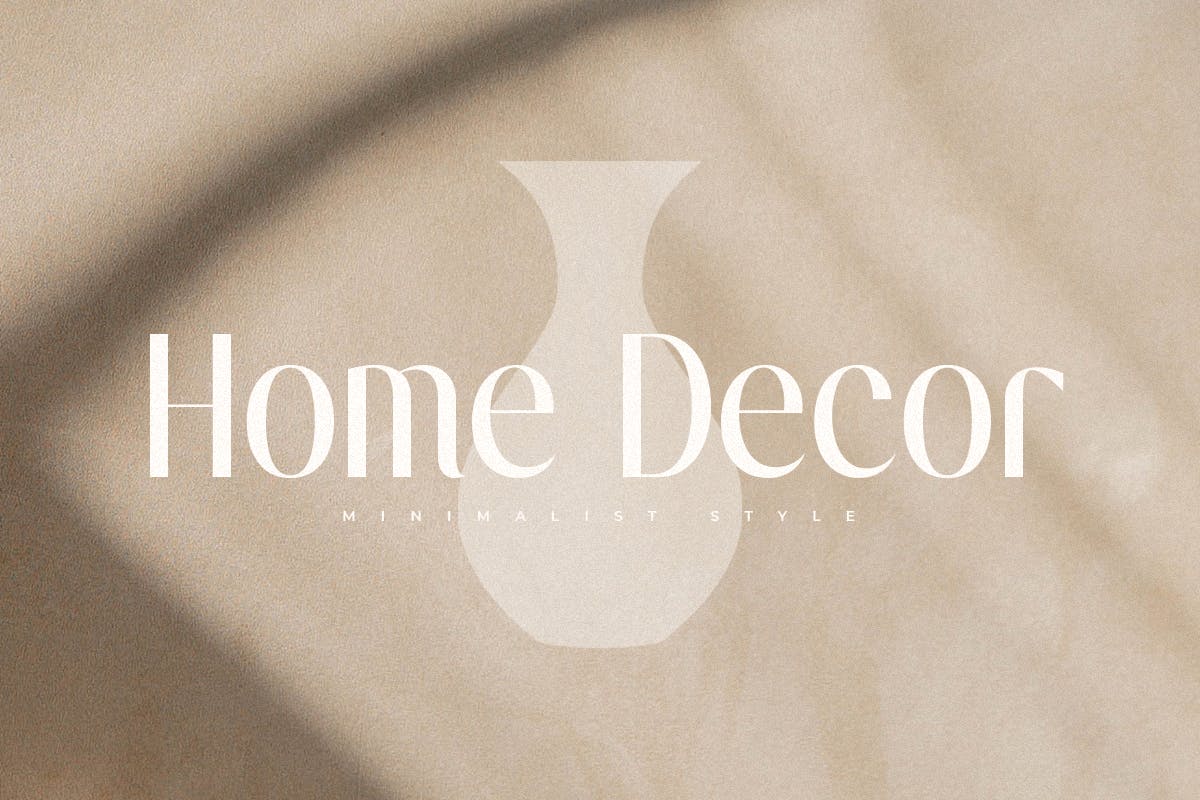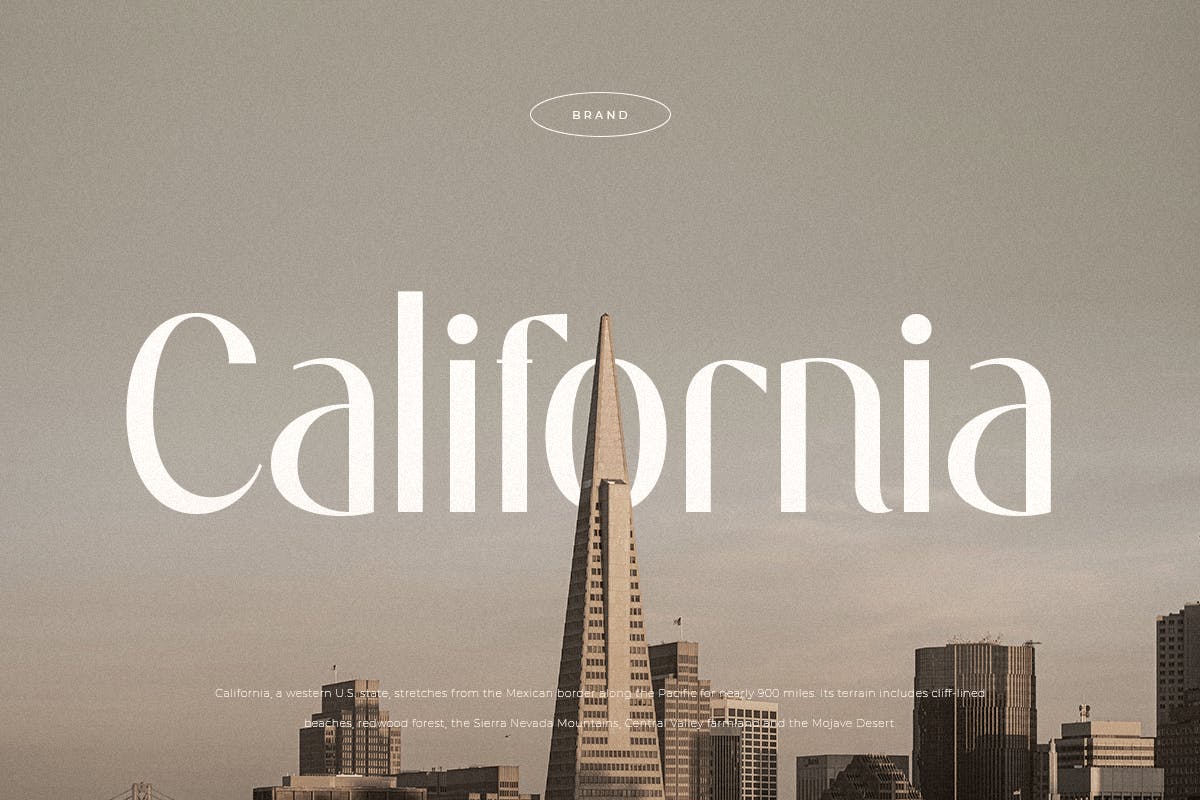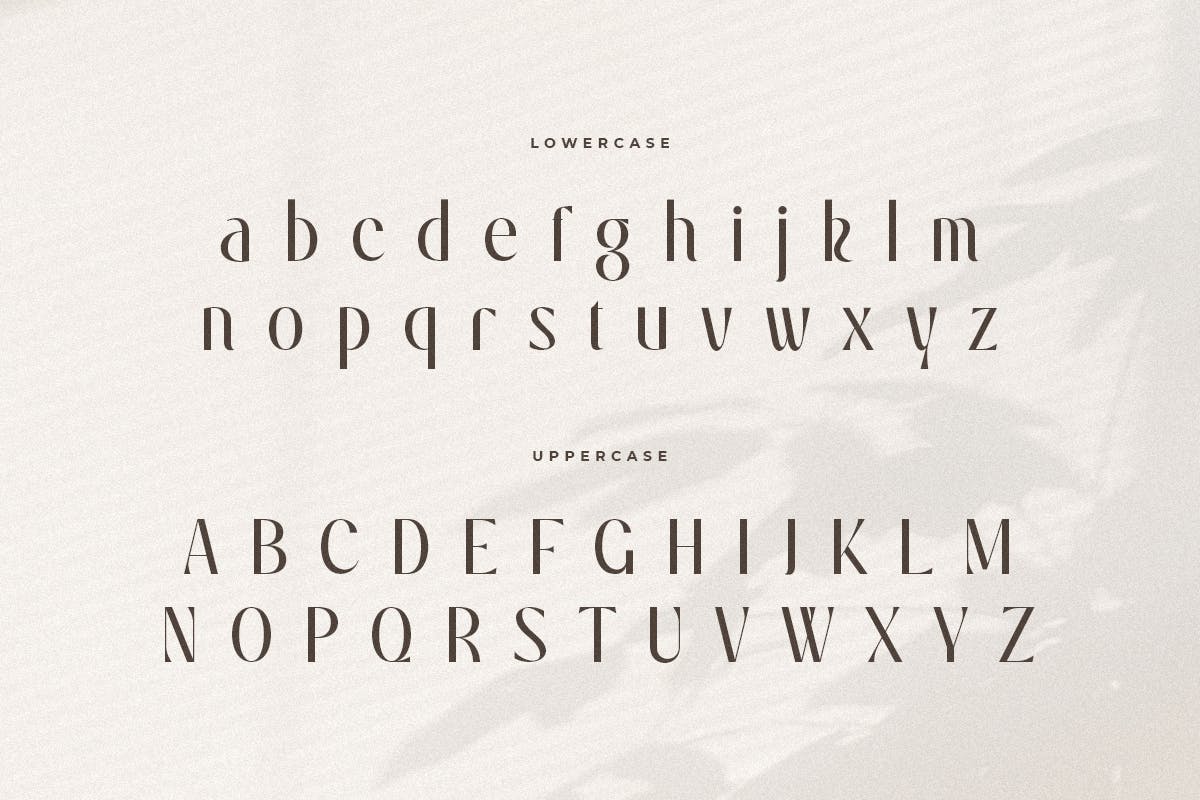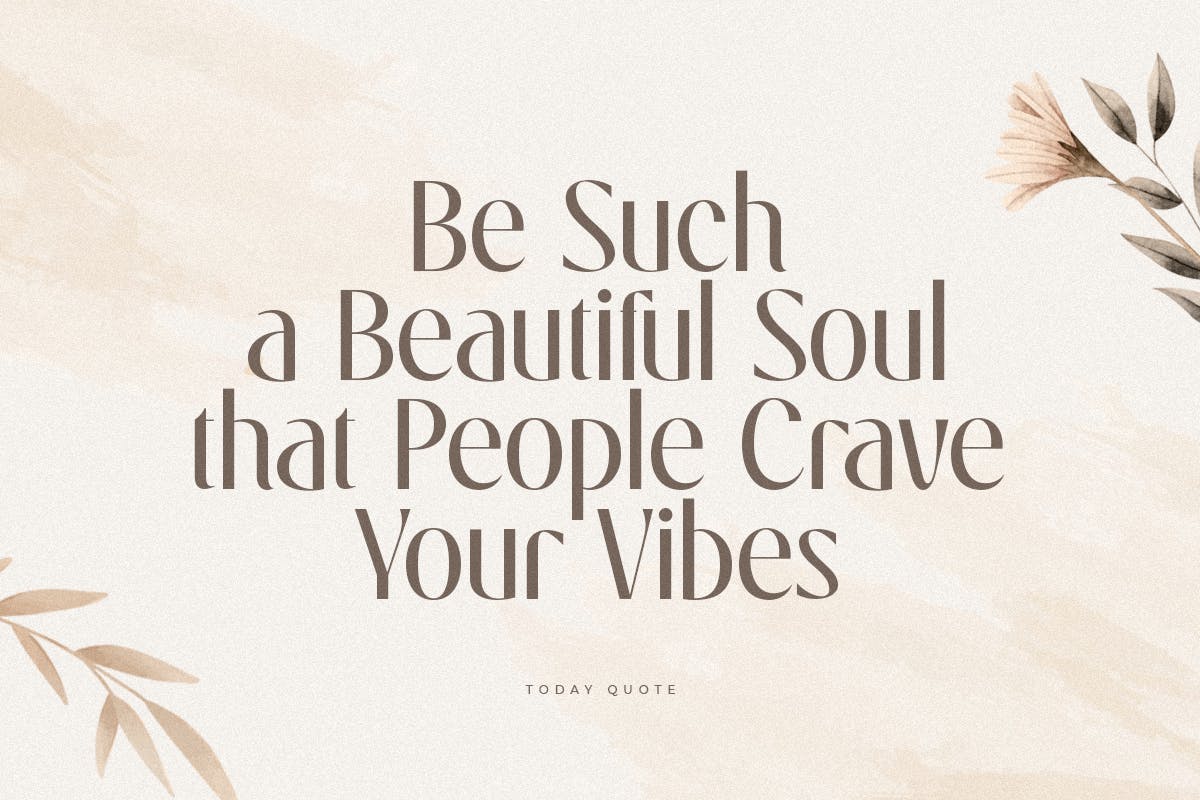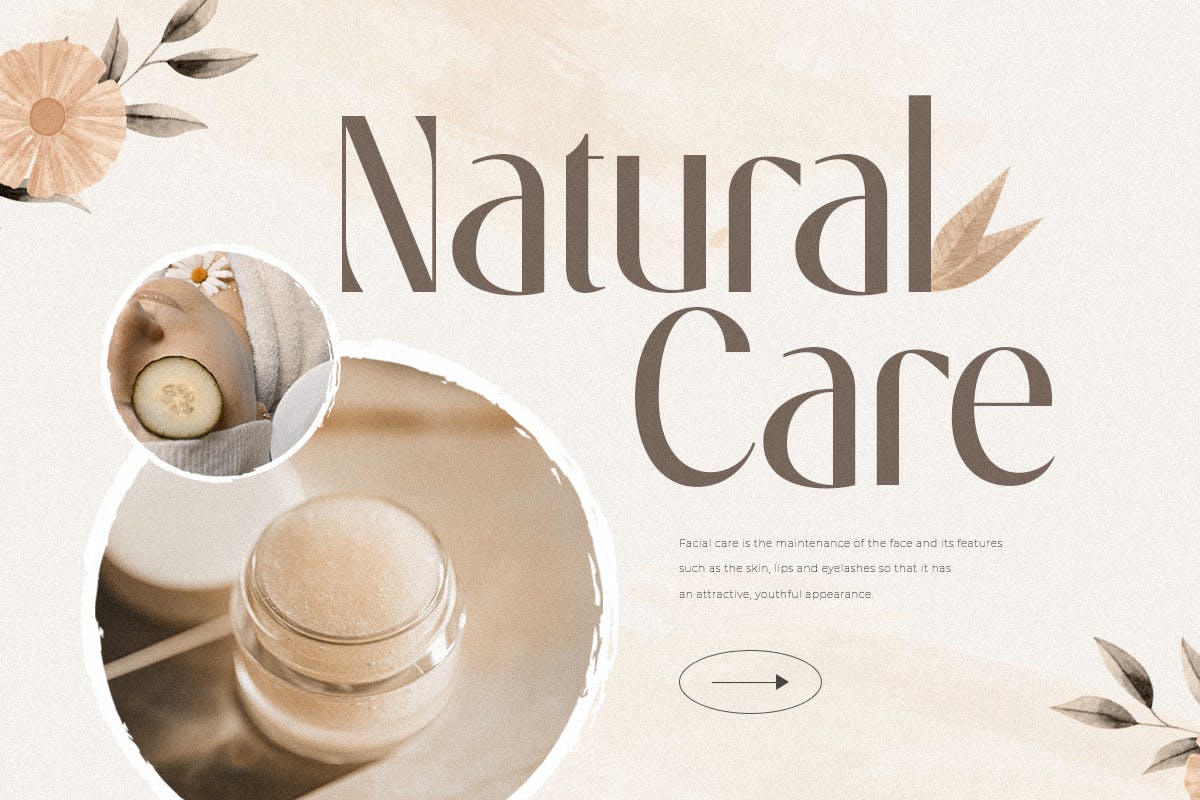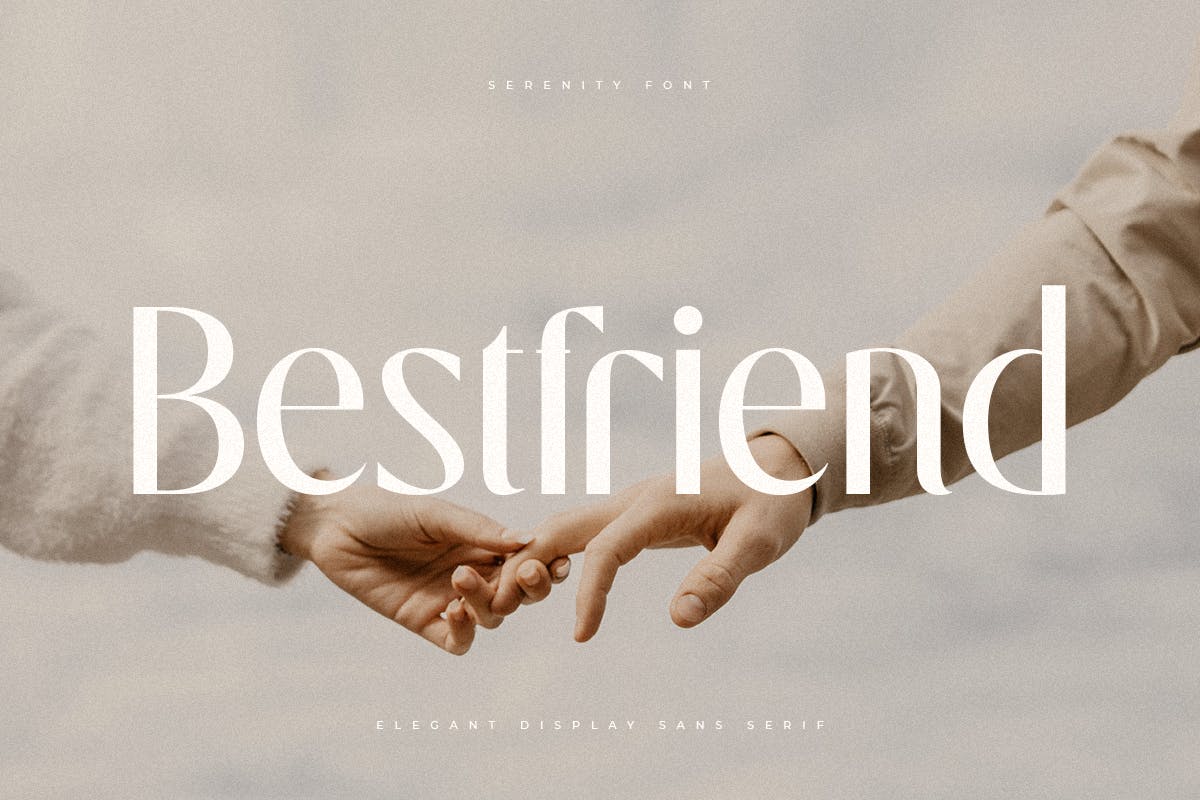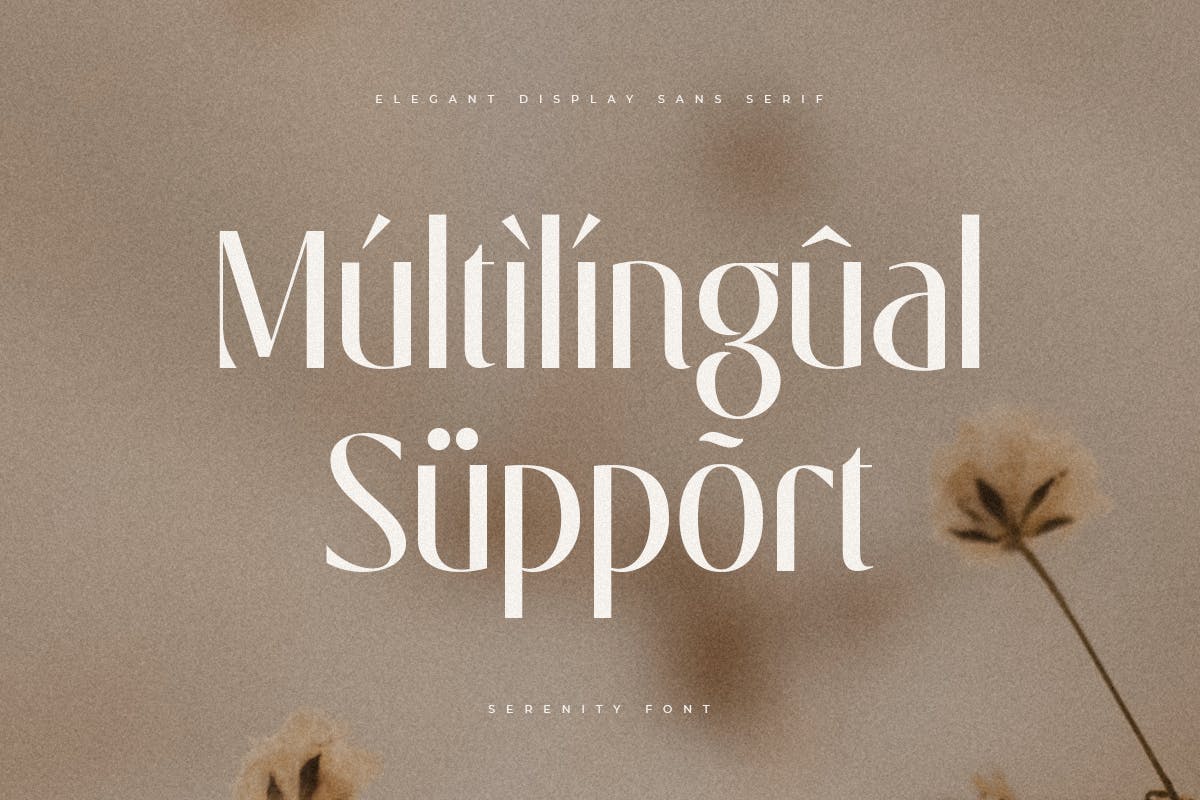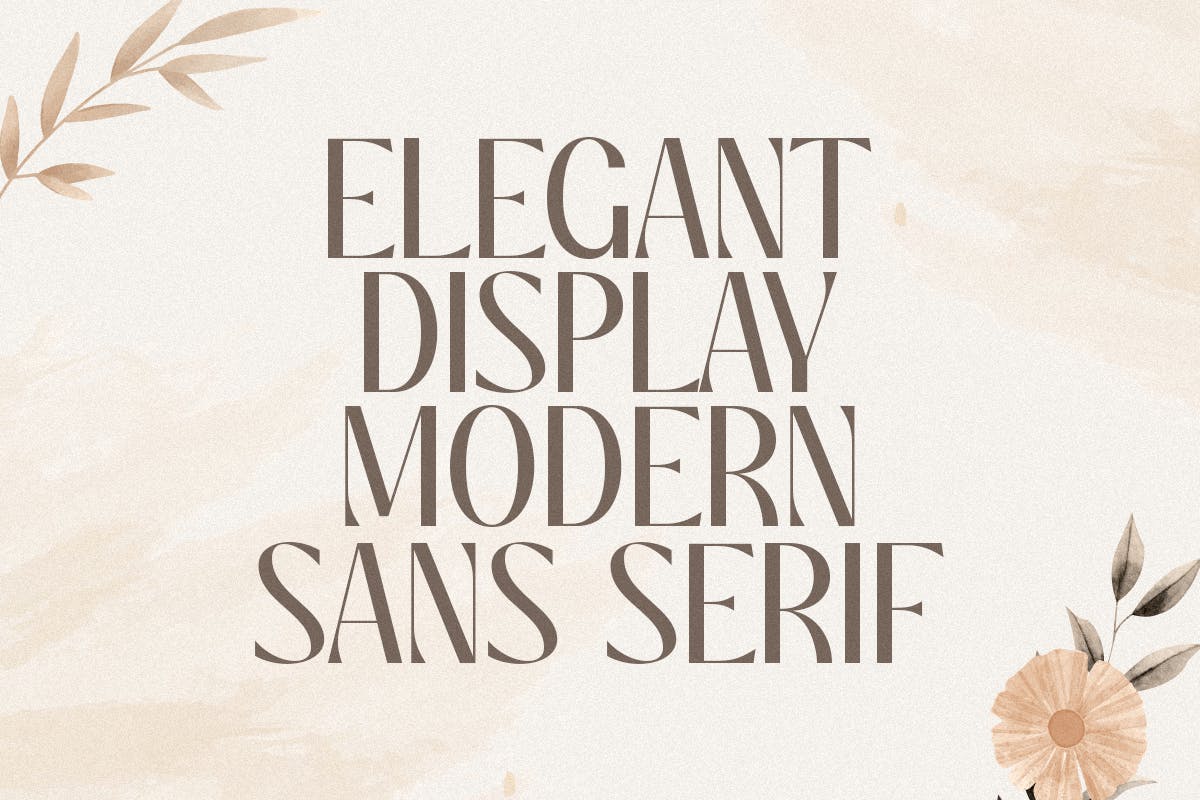
فونت زیبای Serenity Luxury Elegant Beauty یک انتخاب عالی برای نیازهای برندینگ لوکس و شیک است که با طراحی منحصر به فرد خود، ارزش برند شما را افزایش میدهد. این فونت بهخصوص برای طراحان و صاحبان محصولات بسیار مناسب است که به دنبال راهحلهایی برای زیباتر کردن طراحیهای خود هستند. ما برای فونت Serenity، شخصیتهای متنوعی را آماده کردهایم تا به شما در ایجاد واریتههای بیپایان برای نیازهای خلاقانهتان کمک کند.